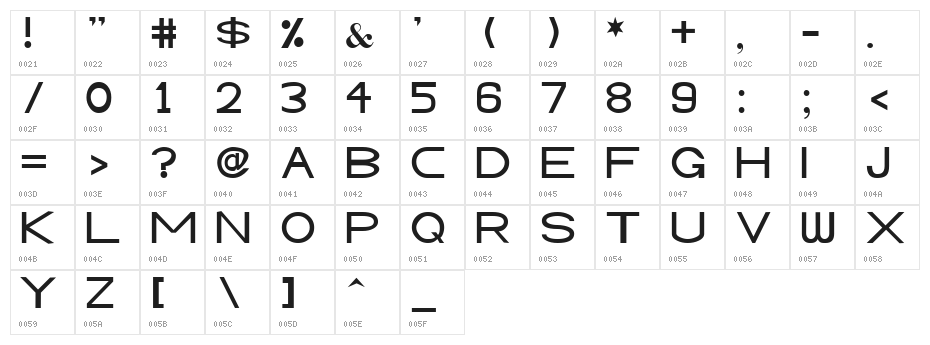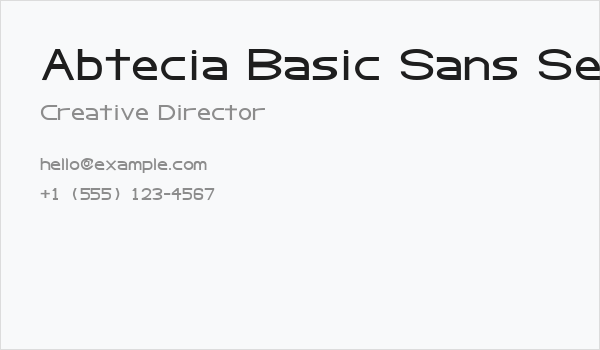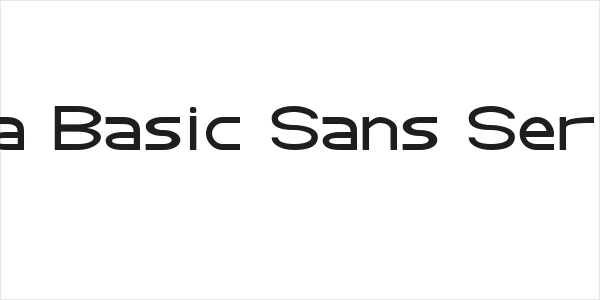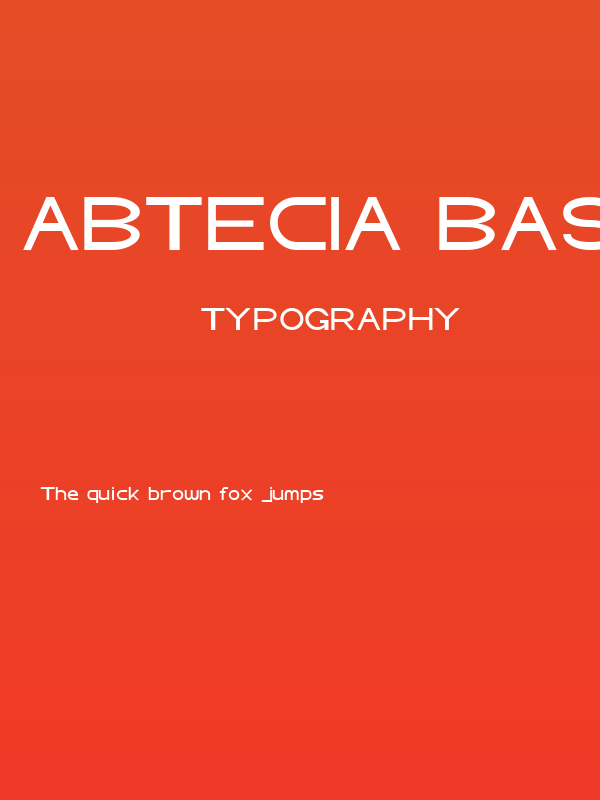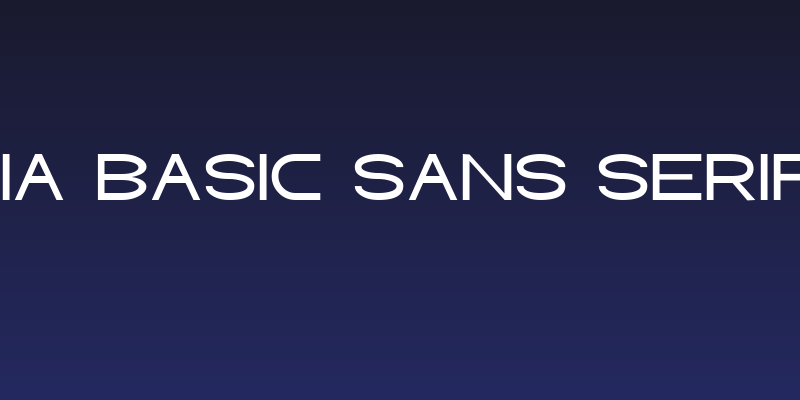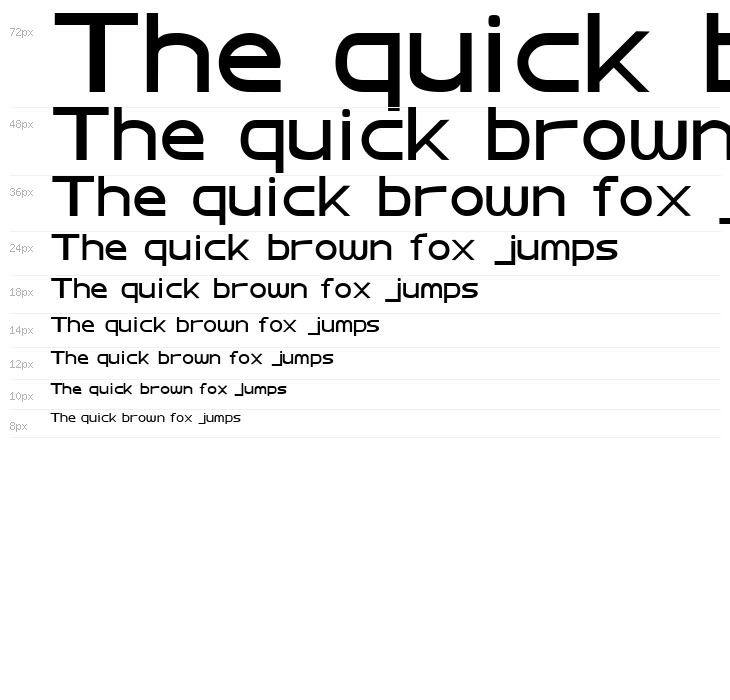
Abtecia Basic Sans Serif Font Font
| Caso de uso | Headlines, Body text, Logos |
| Proyectos propuestos | Ideal for branding, web design, advertising, and editorial projects where a modern and clean look is desired. |